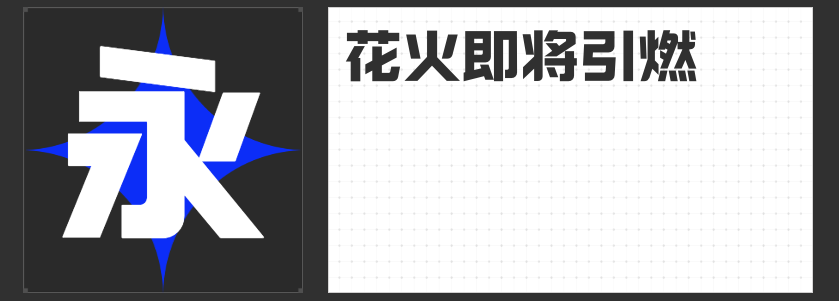
“七一建党节”设计字体推荐:以笔墨颂党恩
在“七一建党节”这一庄重而意义非凡的时刻,设计作品承载着传递红色精神、弘扬爱国情怀的重要使命。合适的字体能让设计更具感染力与表现力,以下四款字体便是为“七一建党节”设计量身打造的佳选。
一、励字开拓者简 特黑
励字开拓者简 特黑字型方正,中宫较大且重心适中,尽显稳重与大气。全部采用直线笔画,横平竖直,棱角分明,简约而不失力量感。起笔和收笔以平切为主,内部几何处理使空间均匀,整体平衡有序。部分钩笔画去钩处理,撇、捺、点竖直化,带来强烈的镜像视觉效果,仿佛象征着党的坚定信念与统一意志,适合用于表现党的坚定领导与开拓进取精神的设计主题。
二、励字勇敢黑简 特黑
励字勇敢黑简 特黑没有衬线装饰,笔划粗壮有力,撇捺等笔画不尖,易于阅读。横直均匀,突出醒目,常用于标题、导语、标志等。在“七一建党节”设计中,它能迅速抓住观众的眼球,传递出党的勇敢无畏与坚定不移,如同党在历史长河中披荆斩棘、勇往直前的精神风貌。
三、造字侠朝凤宋简
造字侠朝凤宋简宽扁工整,软硬兼备、布白均匀。横笔画起笔左下角圆角,收笔处和折笔处方形,撇、捺、提笔画曲线流畅且收笔处切笔凸起,点画为切笔半圆形,钩画外圆内方,兼具力量感与柔美感。这款字体韵美结合,极具表现力,能展现出党的刚柔并济,既有坚定的原则,又有对人民的关怀与温暖。
四、高手兵克侠客体
高手兵克侠客体横笔画起笔、收笔处上扬,如古建筑房顶,充满复古、国潮感。在“七一建党节”设计中,它能唤起人们对历史的回忆,传承党的经典精神,让设计更具文化底蕴与时代特色,仿佛将人们带回到那个波澜壮阔的革命年代。
这四款字体各具特色,能为“七一建党节”设计增添独特的魅力,让红色精神在设计中得以完美呈现。